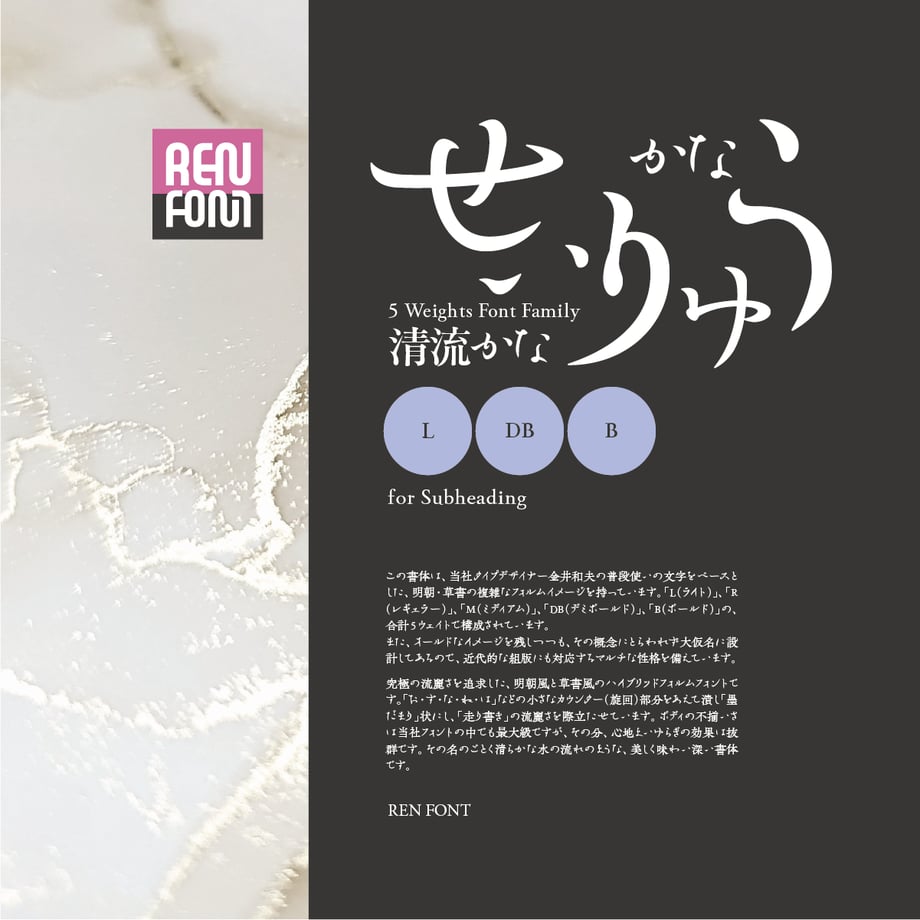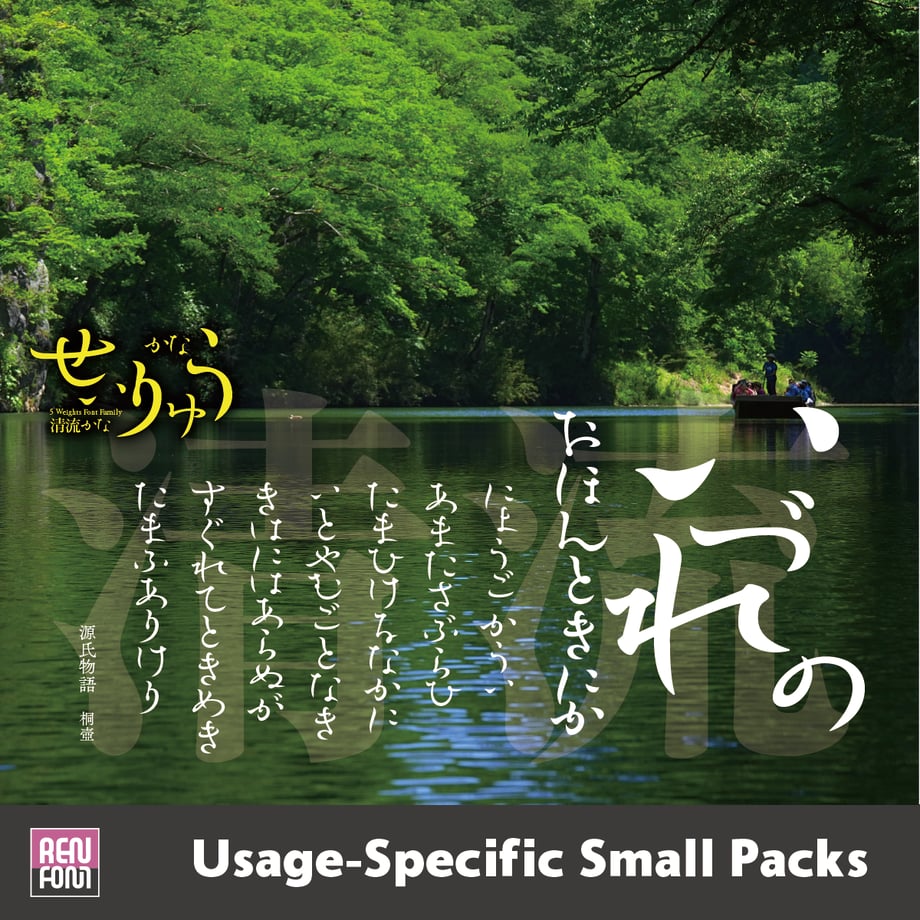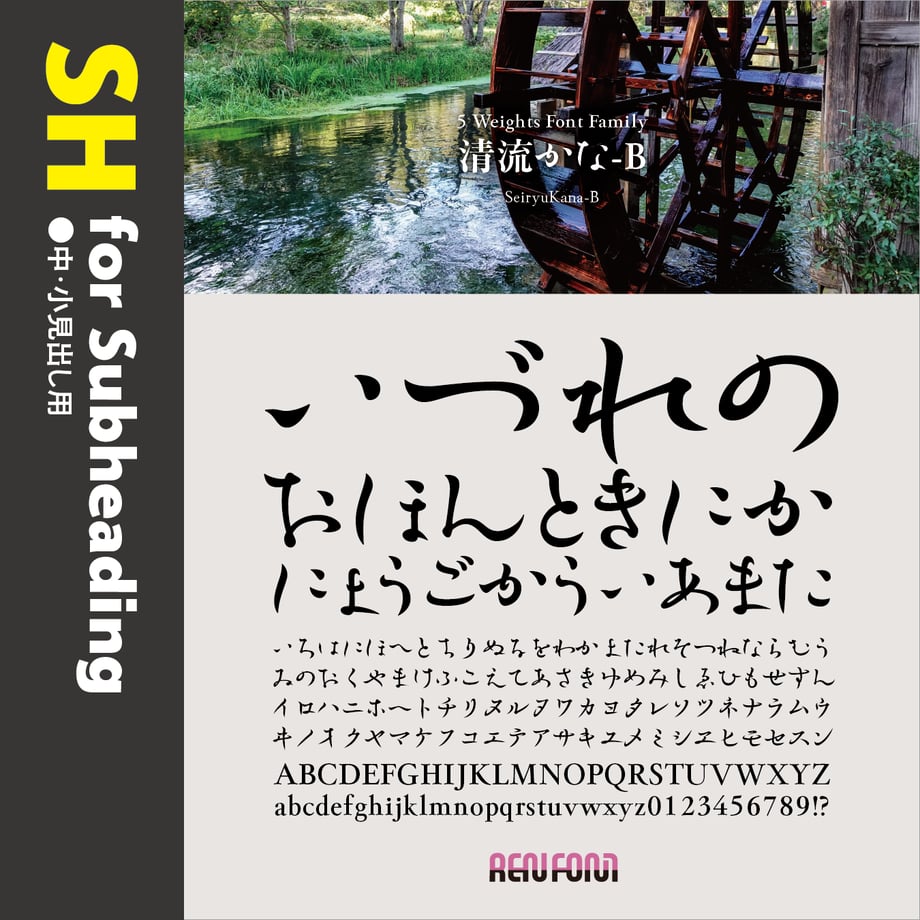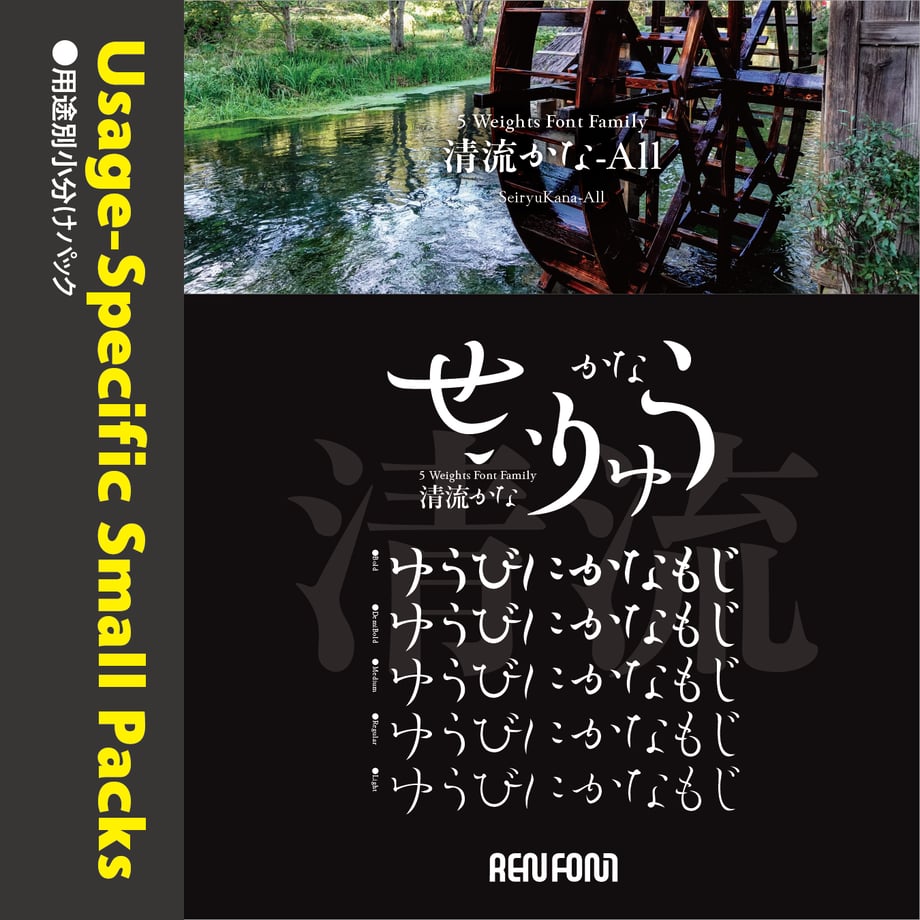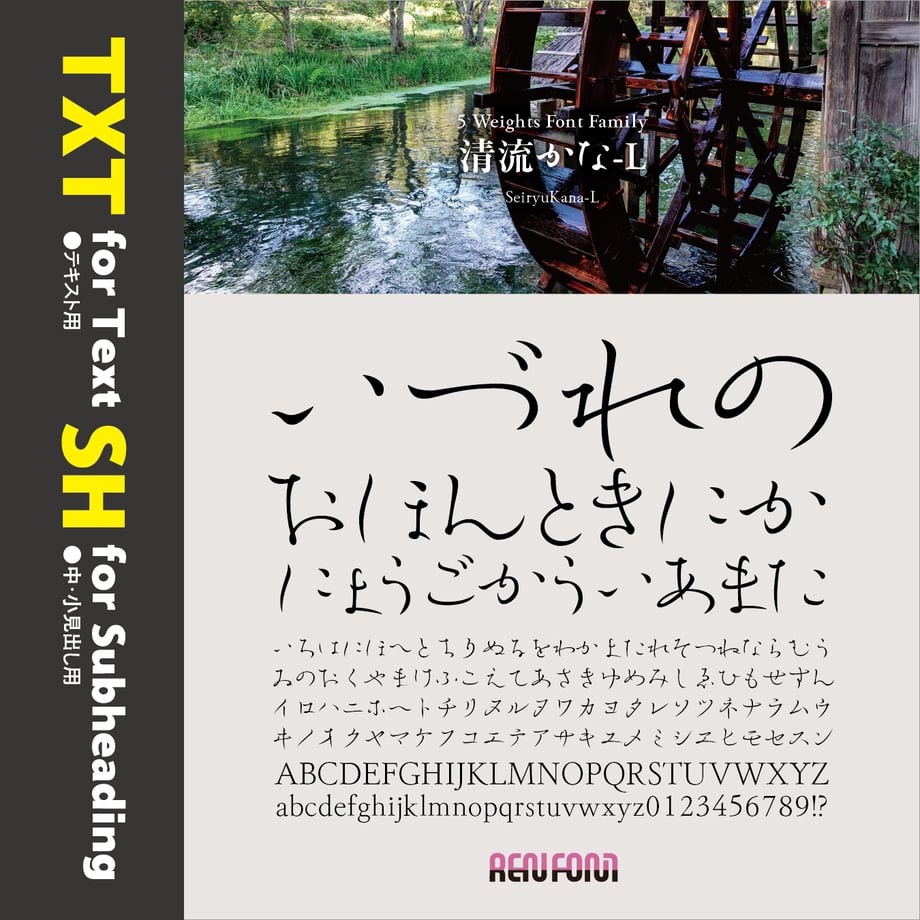
清流かな-SH(中・小見出し用)L/DB/B
横方向を意識した異色な書体
清流かな 5ウェイトファミリー / OpenType
コンセプト
平安歌人の情念に思いを馳せて…
清流かなファミリーの各書体は、
草書体を意識したフォルムを備えています。かな文字の成り立ちである草書体。清流かなは、草書の走り書きの妙とも言うべき流麗さに、明朝の要素を加味して作り上げています。縦組み、横組みともプロポーショナル加工を加えました。また、ペアカーニングも緻密にほどこしてあります。
この書体は、当社タイプデザイナー金井和夫の普段使いの文字をベースとした、明朝・草書の複雑なフォルムイメージを持っています。「L(ライト)」、「R(レギュラー)」、「M(ミディアム)」、「DB(デミボールド)」、「B(ボールド)」の、合計5ウェイトで構成されています。
また、オールドなイメージを残しつつも、その概念にとらわれず大仮名に設計してあるので、近代的な組版にも対応するマルチな性格を備えています。
心地よいゆらぎの効果を追求した書体
究極の流麗さを追求した、明朝風と草書風のハイブリッドフォルムフォントです。「お・す・な・ね・は」などの小さなカウンター(旋回)部分をあえて潰し「墨だまり」状にし、「走り書き」の流麗さを際立たせています。ボディの不揃いさは当社フォントの中でも最大級ですが、その分、心地よいゆらぎの効果は抜群です。その名のごとく清らかな水の流れのような、美しく味わい深い書体です。
他社「総合書体」との「共存」
現在、世の中に出回っているフォントの数はすでに数え切れないほどになっています。明朝体に限ってもまた然り。
清流かなは5ウェイトありますが、それぞれの太さにさほどの差がありません。本来は3ウェイト展開にすべきかも知れませんが、あえて5ウェイトにしたのにはそれなりの理由があります。
かなフォントは、単独ではあまり存在意義はありません。漢字と組み合わせてはじめて「意味」が生じます。
フォントのウェイト呼称は、ほとんどのベンダが「ライト」から「ウルトラ」に至る7から9ウェイト展開をしています。ただ、それぞれの太さに明確な基準はなく、各ベンダの判断によります。ですので、例えば「ライト」でも太さが微妙に異なってきます。かなフォントがそれに対応するには、細かいウェイト展開が必要となります。
当社かなフォントの細かいウェイト展開は、それが理由です。お好みに合わせて合成フォントをお楽しみいただければ幸いです。
日本語文章の約70%はひらがな、カタカナが占めているといわれます。それだけに紙面の雰囲気を左右し、決定づける重要なアイテムです。
清流かなのウェイトは5つ。本来、長文に向かない書体ですが、伝統的なオールド書体の雰囲気も持ち合わせており、一番使用頻度の高いLウェイトも制作しました。微妙な太さの違いがあるので、用途は意外に広いかも知れません。
そのフォルムは、しなやかでなめらか。終筆は横方向を意識しており、不揃い極まりないボディにもかかわらず横組に効果を発揮します。先端は全て丸く処理しました。カタカナは、その最大の特徴である「直線的フォルム」を残し、ひらがなの曲線を加味しバランスを取るという難しさにあえて挑戦した野心作となっています。
欧文・数字は、奔放な両かなとは異なり、クセの少ない伝統的なイメージにデザインしました。わずかに「K」「Q」「R」のテールに「かな」の雰囲気を持たせてあります。
格調高いGaramond調の形状ですが、若干現代風な設計になっています。欧文書体としての単独使用にも十分に耐えうる、和文付嘱書体としては稀な、非常に高い完成度を持っています。